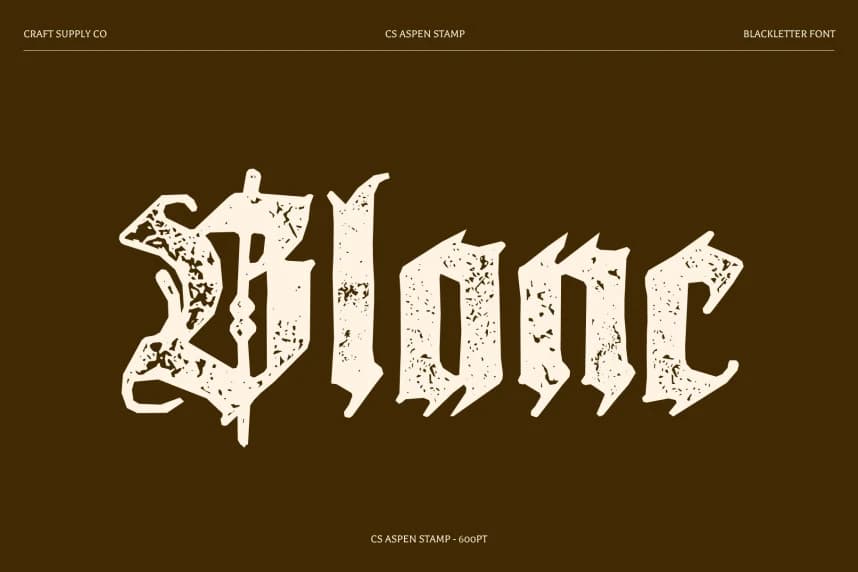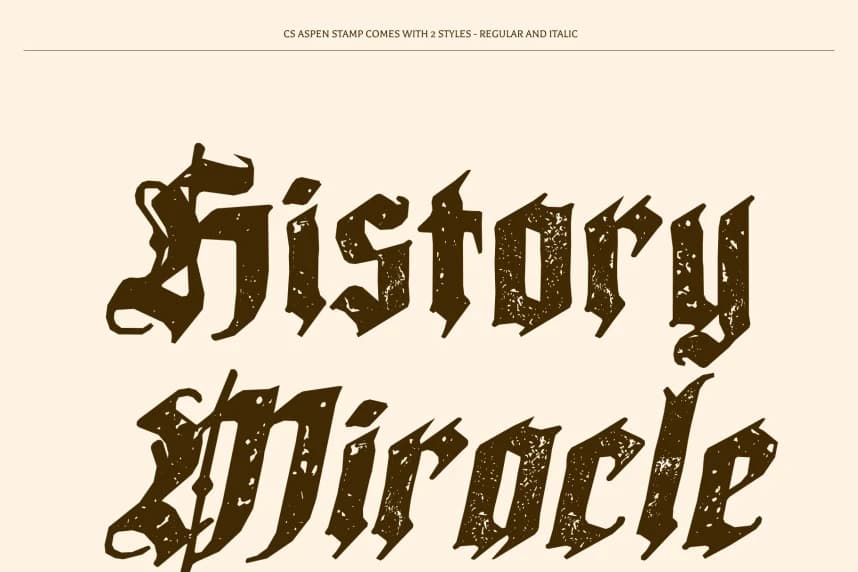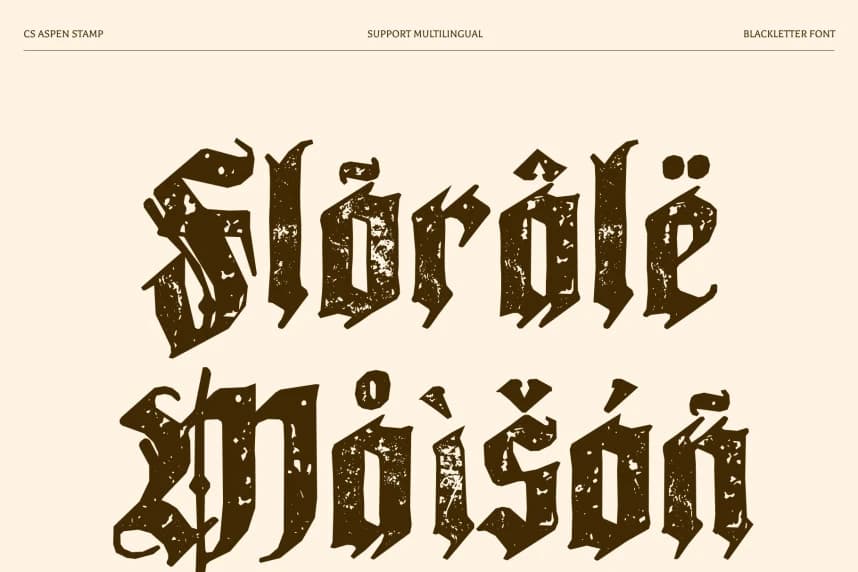
CS Aspen Stamp Font
CS Aspen Stamp Font – Blackletter Görkemi, Dokulu Otoriteyle Klasik Gotik Stil, Damgalı Bir Bitişe Sahip. Bu, geleneksel Blackletter zarafetini ince dokulu damgalı bir dokuyla güçlendirerek antik karakterini daha da zenginleştirir.
CS Aspen Stamp Font – Dokulu Otoriteyle Blackletter Grandeur, Klasik Gotik Stil, Damgalı Bir Bitişe Sahip. Bu, geleneksel Blackletter zarafetini ince, damgalı bir doku ile güçlendirir ve antik karakterini pekiştirir.
CS Aspen Stamp